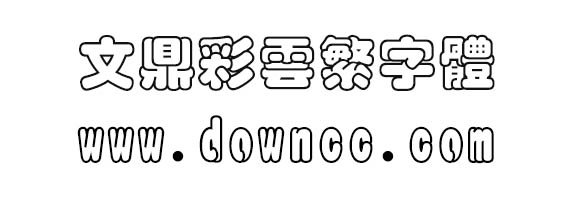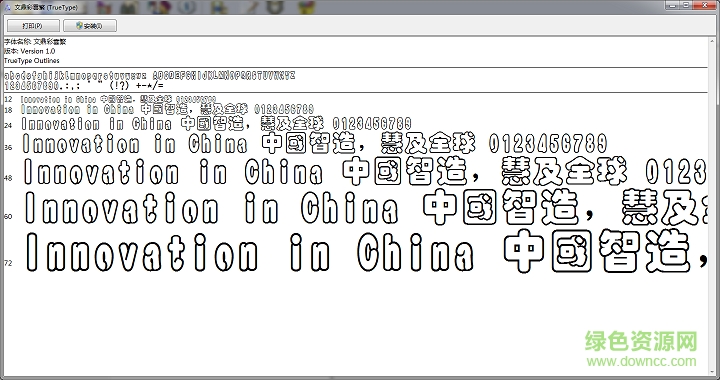
文鼎彩云繁是一款空心繁體字體,整個(gè)字體有部分的重疊的,看起來非常緊促,廣告設(shè)計(jì)、藝術(shù)創(chuàng)作中經(jīng)常用到。趕快大到綠色資源網(wǎng)下載體驗(yàn)吧!
文鼎彩云繁是一種空心字,就無名字一般彩云,就給呈現(xiàn)出一種輕飄飄的感覺,感覺時(shí)刻都有可能飛走的樣子